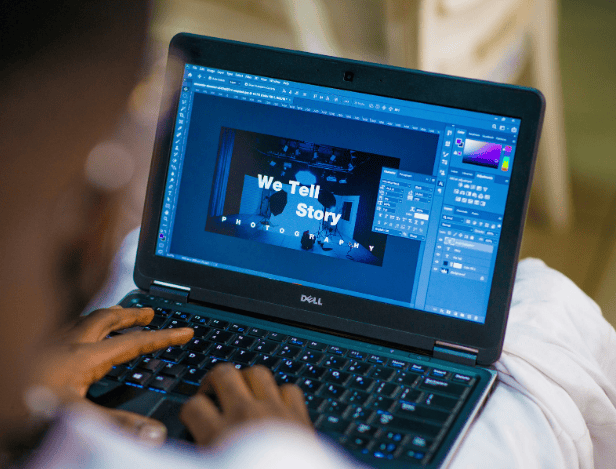
L'IA révolutionne la typographie
L’IA fascine et bouscule les métiers de la création visuelle, y compris le graphisme, historiquement fondé sur l’œil et l’intuition humaine. Dans une école graphisme comme Studio M Vannes, cette technologie n’est pas vue comme une menace, mais comme un outil à apprivoiser. Utilisée avec discernement, elle devient un allié créatif et invite les futurs designers à repenser leur manière de concevoir et de créer.
l’IA révolutionne la typographie graphique
La typographie a toujours été le miroir des époques, et elle a surtout évolué avec la technologie. Aujourd’hui, l’arrivée de l’IA a marqué une nouvelle étape. Il est possible de générer en quelques secondes des polices personnalisées, l’IA permet aussi d’analyser les tendances visuelles, d’adapter les caractères à une marque ou une émotion qu’on a souhaité donner.
Pendant les cours de l’école de graphisme chez STUDIO M Vannes, on apprend à nos étudiants à comprendre comment fonctionne le dialogue entre cette intelligence artificielle et l’humain. On apprend à nos étudiants comment un algorithme peut produire une typographique originale, mais on leur apprend surtout que l’IA peut proposer des choses, mais c’est au designer de choisir, la sensibilité humaine est essentielle.
Les étudiants en école de graphisme ont la possibilité d’utiliser une large palette d’outils comme des générateurs de polices, des logiciel de design graphique, ou encore des plateformes de mise en page intelligente. Mais à STUDIO M Vannes l’accès est surtout mis sur la compréhension critique de son travail et de ses outils, L’IA peut aider à produire, elle peut être un partenaire de réflexion, mais ce n’est pas à elle de faire tout le travail.
L’enseignement de l’intelligence artificielle
Durant les cours à STUDIO M Vannes, les étudiants ont la possibilité de mettre ces concepts en pratique, ils font de la création de typographie expérimentale, refonte d’identité visuelle via l’IA, de la conception d’affiches interactives ..
Chaque projet qu’ils font pendant les cours est une expérience complète, qui laisse la place à de la réflexion éthique, de la recherche et de la conception. On apprend à nos étudiants à se questionner sur la propriété intellectuelle, ce qui est aujourd’hui un enjeu plus qu’important avec l’IA.
Dans une école de graphisme comme Studio M Vannes, la pédagogie s’adapte : les étudiants réalisent des projets collaboratifs où humains et IA co-conçoivent des identités visuelles. Ce travail en binôme homme-machine développe la curiosité, l’adaptabilité, et une meilleure compréhension des limites techniques. Le résultat ? Des designers capables d’allier création intuitive et innovation numérique.
IA et créativité
Malgré la puissance de l’IA, la typographie reste une affaire d’émotion. La typographie qu’on utilise pour créer un design porte une personnalité, que seule la vision humaine est capable de mettre en lumière.
C’est pourquoi les cours à STUDIO M Vannes ne s’arrêtent pas à la technologie. Les étudiants ont des cours de dessin, de composition et de culture visuelle qui permettent de nourrir l’imagination de chacun. Les étudiants apprennent à utiliser l’IA mais sans s’y soumettre, ils gardent leur patte artistique, et développent un œil critique qui leur permet de voir la différence entre une création générée par de l’IA et une œuvre pensée.
Aujourd’hui l’IA commence à prendre une place importante dans nos vies, les entreprises cherchent de profils capables de jongler avec la machine tout en gardant une vision artistique forte. Maitriser l’IA devient un atout stratégique qui permet de renforcer l’employabilité des jeunes diplômés issue de STUDIO M Vannes.
Pourquoi choisir STUDIO M Vannes ?
Choisir STUDIO M Vannes, c’est choisir une école qui se distingue par une pédagogie équilibrée entre technologie et sens artistique. Nos étudiants apprennent à travailler sur des projets de cas concrets avec de réelles entreprises, ils sont confrontés à des demandes qu’ils pourront avoir en entreprise, et en apprenant à utiliser des outils d’IA récents comme Midjourney, Adobe Sensei ou Fontjoy.